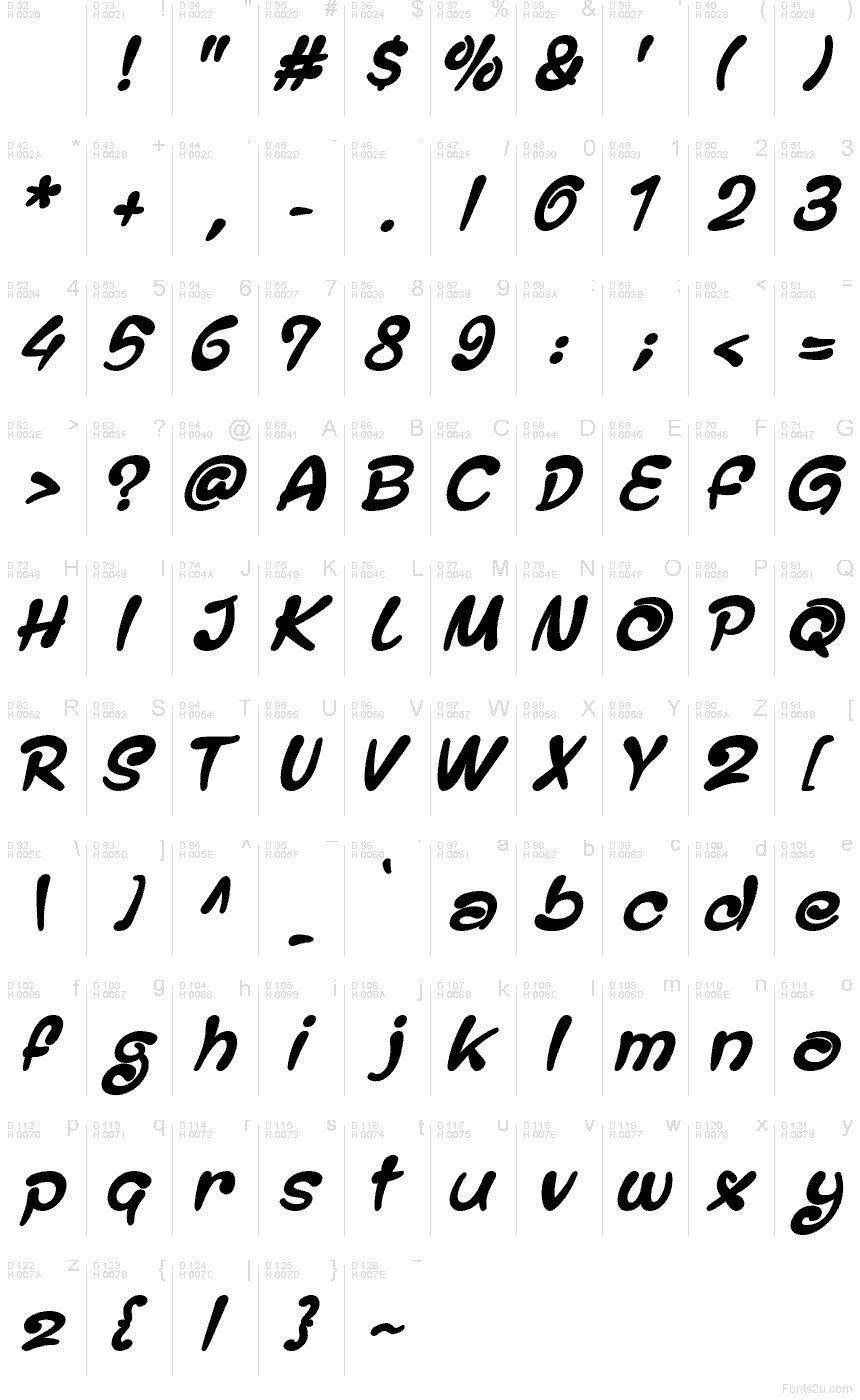
Oligeb von Ari Juanda ist eine kostenlose, im Groovy-Stil gehaltene Display-Schrift mit breiten, geschwungenen Strichen und einer markanten Retro-Silhouette. Abgerundete Buchstaben rollen sich nach innen ein, wodurch tropfenförmige Öffnungen und lebhafte Strichstärkenwechsel entstehen.
Musik und Mode im Stil der Siebzigerjahre sind ihr vertrautestes Terrain, wodurch sie sich gut für Albumcover, Eventplakate und Textildrucke eignet. Ihre geschwungenen Formen prägen auch Lebensmittelverpackungen oder das Branding von Cafés mit einer warmen, leicht exzentrischen Note. Sie richtet sich an Designer und Marken, die nach Gestaltungen suchen, die an psychedelische Grafik ohne abgenutzte Texturen erinnern.